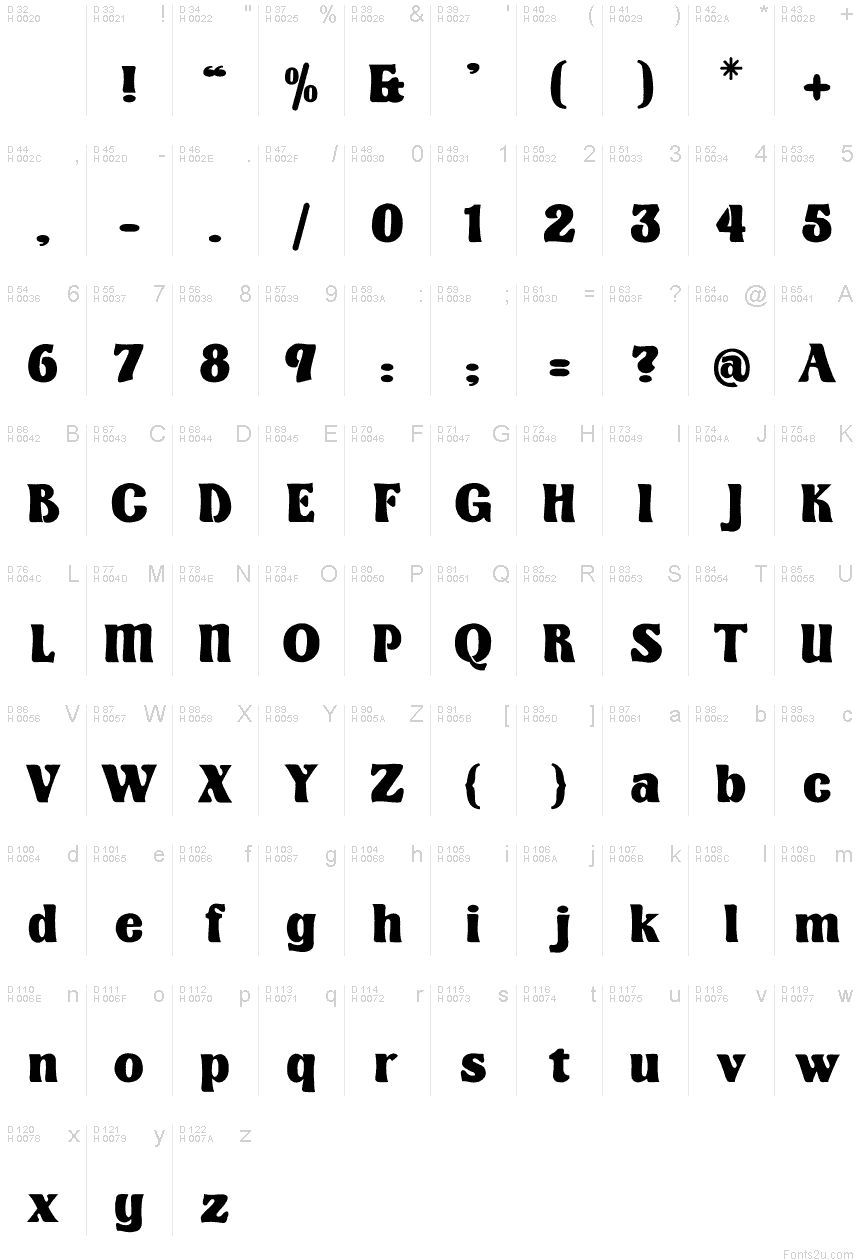
由 Kevin King 设计的 Kingthings Organica 是一款免费的装饰性衬线字体,带有美妙的、充满手工质感的摇曳感。其厚实的笔画、圆润的边角和略显不规则的曲线,仿佛是在软木上雕刻或用浓墨按压而成,赋予每个字词一种质朴且亲切的分量感。字符排布紧凑,营造出一种既俏皮又稳重的粗犷纹理。
使用 Kingthings Organica,您的标题瞬间就能流露出手工感,非常适合生态品牌、有机产品包装、咖啡馆菜单、自然主题海报、童书封面以及手工艺博客。这款免费字体在节日或市集传单上也同样出彩,能为您想要传达的温暖感加分,而不会显得杂乱。建议在小字正文搭配一款简洁的无衬线字体,并让 Kingthings Organica 在大标题中尽情发挥,以实现迷人感与清晰度的完美平衡。
An 'organic style font originally designed in 1981